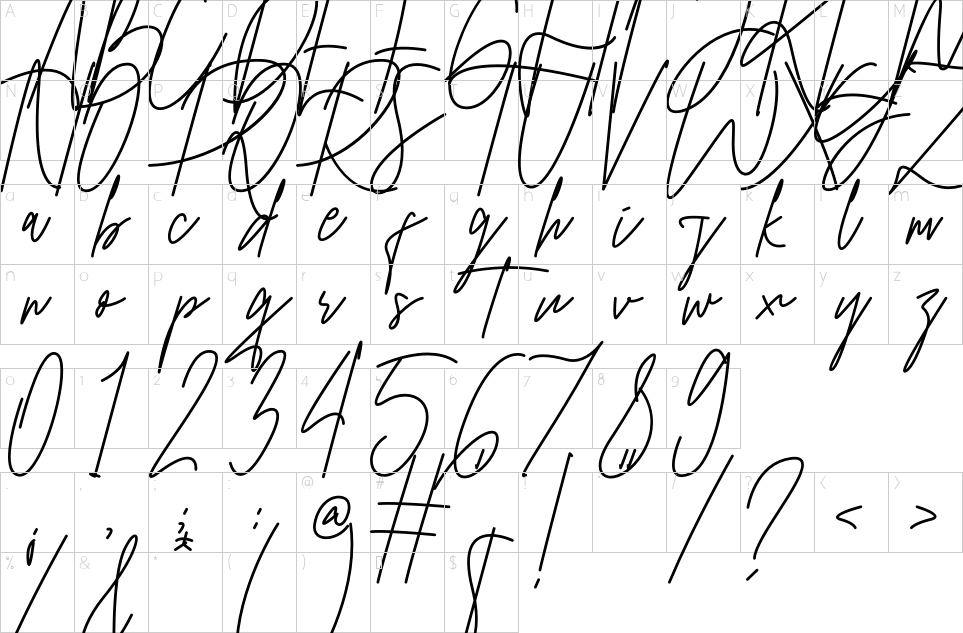
Pakotha é uma fonte gráfica que oferece um equilíbrio perfeito entre elegância e simplicidade. Desenvolvida pelo designer Jada Akbal, esta fonte foi criada para atender às necessidades de designers e desenvolvedores de sites em busca de uma fonte limpa e versátil. Com uma aparência natural e versátil, Pakotha é uma escolha excelente para criar materiais digitais de alto nível. Seu design cuidadosamente elaborado torna Pakotha uma escolha atraente para qualquer aplicação de design, seja ela um projeto de interface de usuário, um logo ou até mesmo uma capa de livro. Com sua disponibilidade gratuita para Windows e Mac, Pakotha é uma fonte que merece uma posição em sua biblioteca de fontes. Com uma sólida base de usuários, este é um dos motivos de sua popularidade e é sem dúvida uma excelente adição para qualquer coleção de fontes.